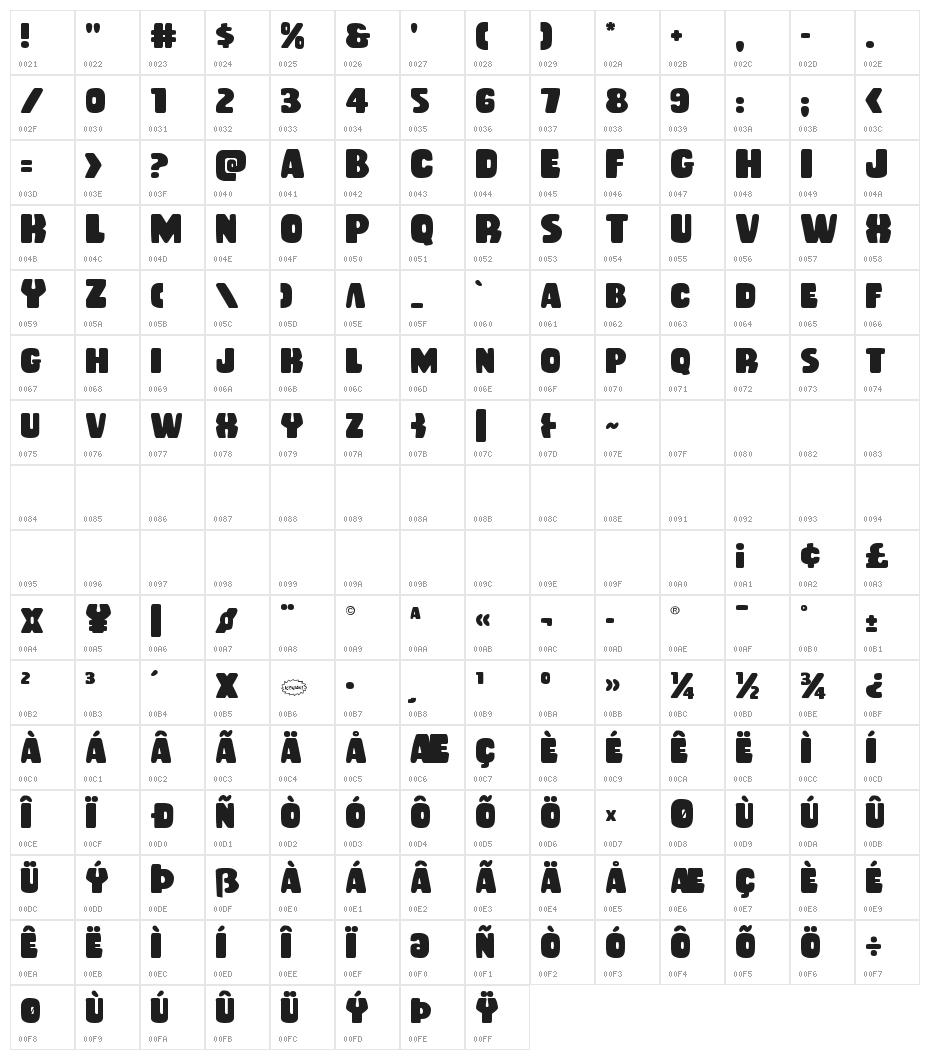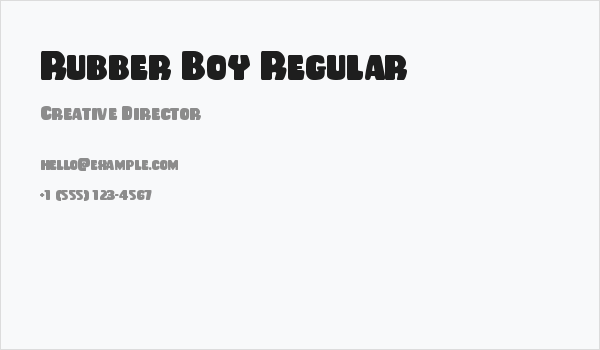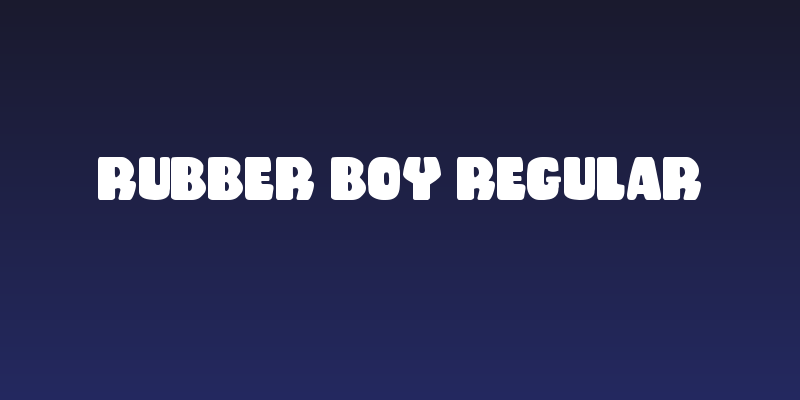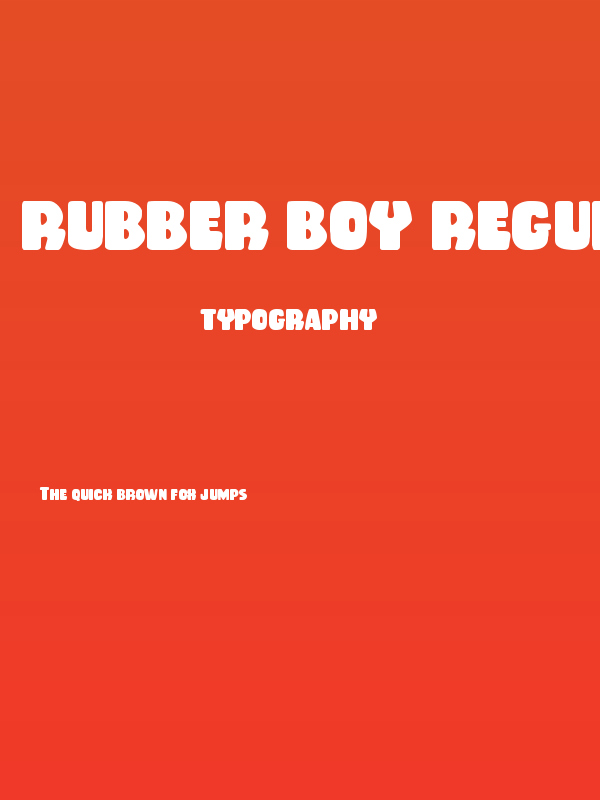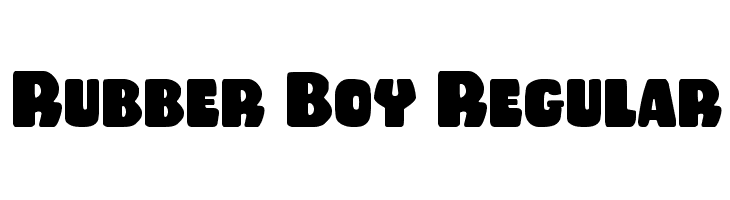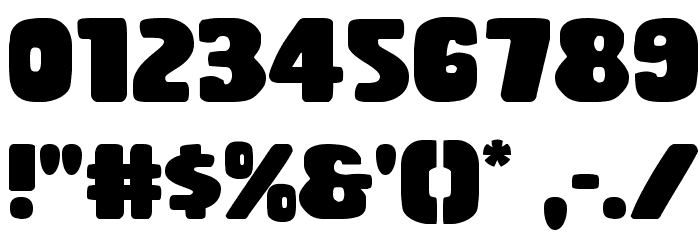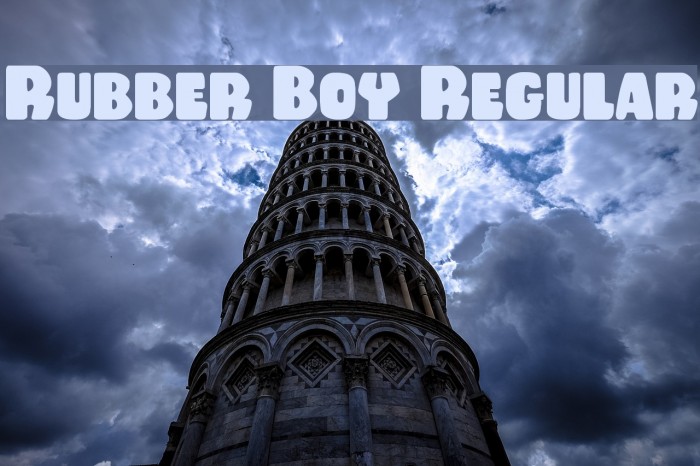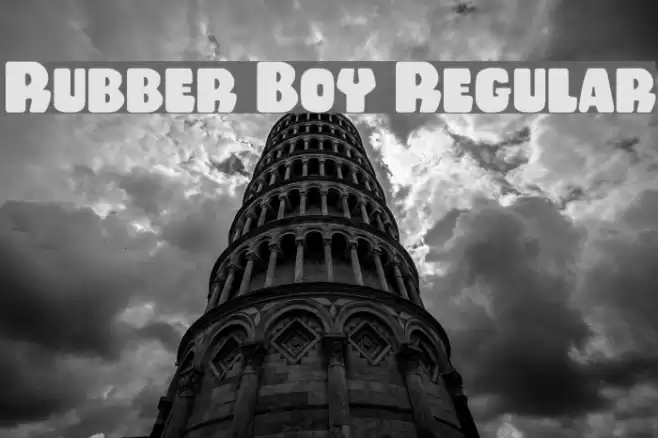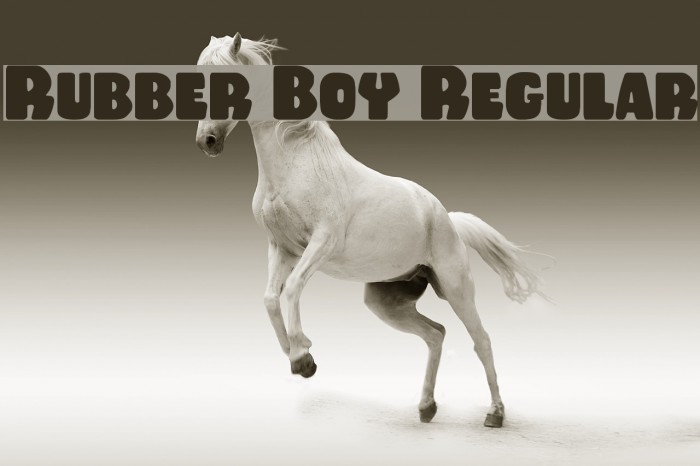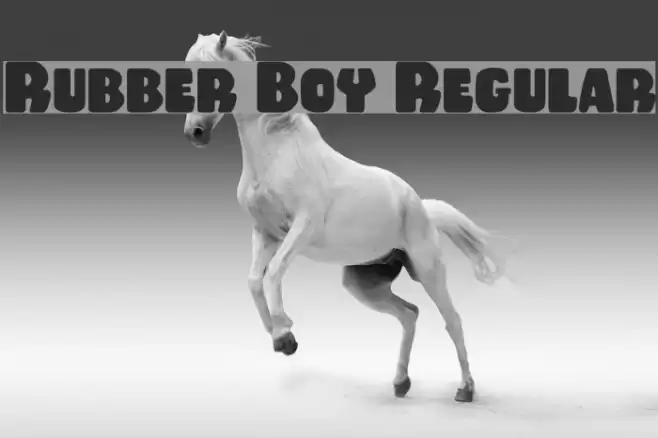
Rubber Boy Regular Font
| समग्र शैली | Playful, Retro |
| उपयोग का मामला | Headlines, Logos, Posters |
| सुझाए गए प्रोजेक्ट | Ideal for children's books, playful branding, posters, and any project requiring a fun, approachable aesthetic. |